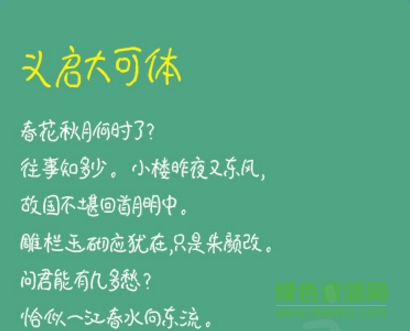
義啟大可體字體是一款義啟類手寫風(fēng)格字體軟件,字體整體效果看起來無拘無束,非常的自由,筆畫看似隨意,卻透露出非常歡快的心情,喜歡大可體的朋友歡迎來綠色資源網(wǎng)下載體驗(yàn)!
義啟大可體來自于廣大喜歡義啟字體的粉絲大可之嘔心力作。這是一款極具個(gè)人特色的手寫體,也是粉絲在義啟字庫定制的第一款手寫體。